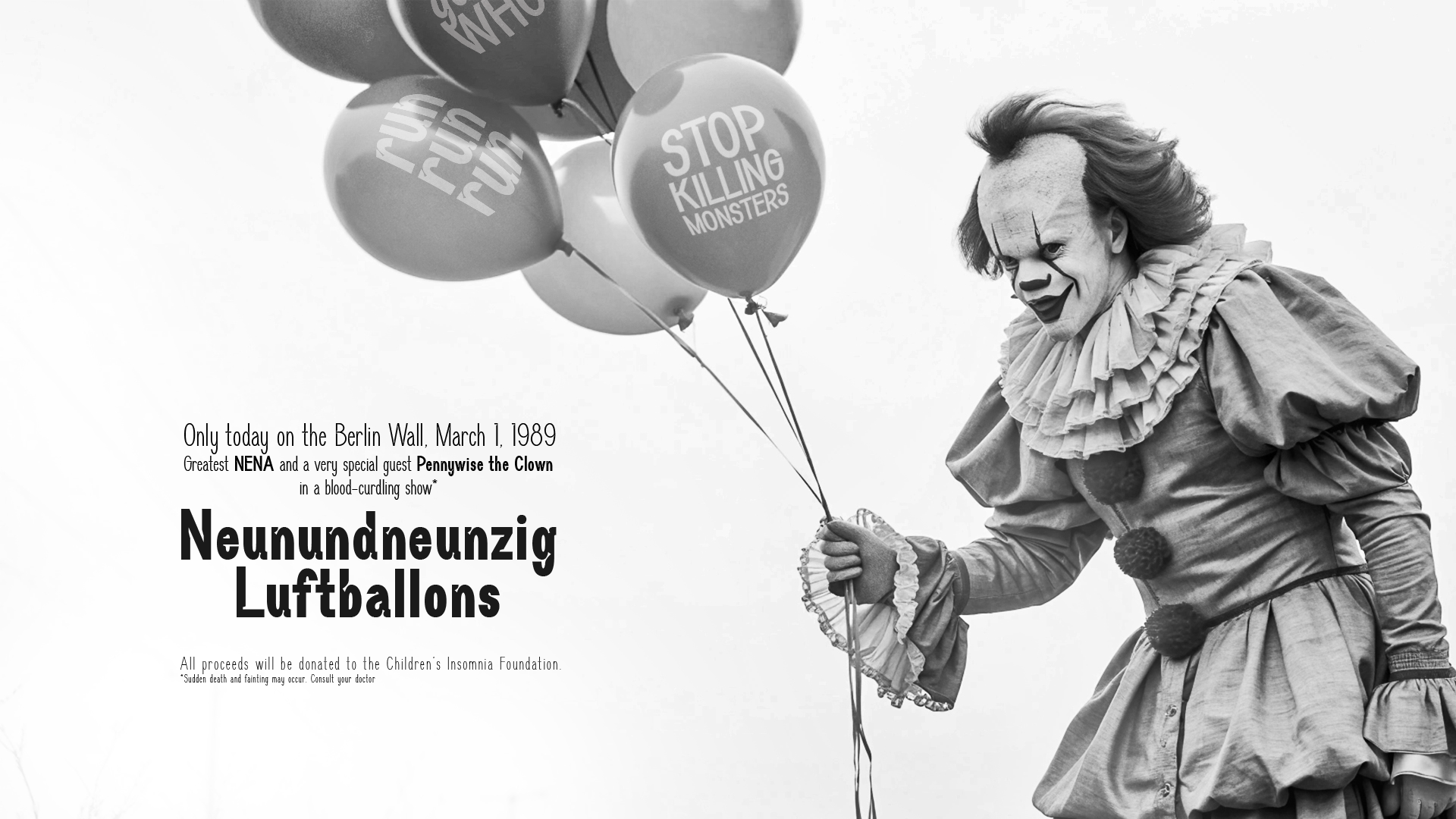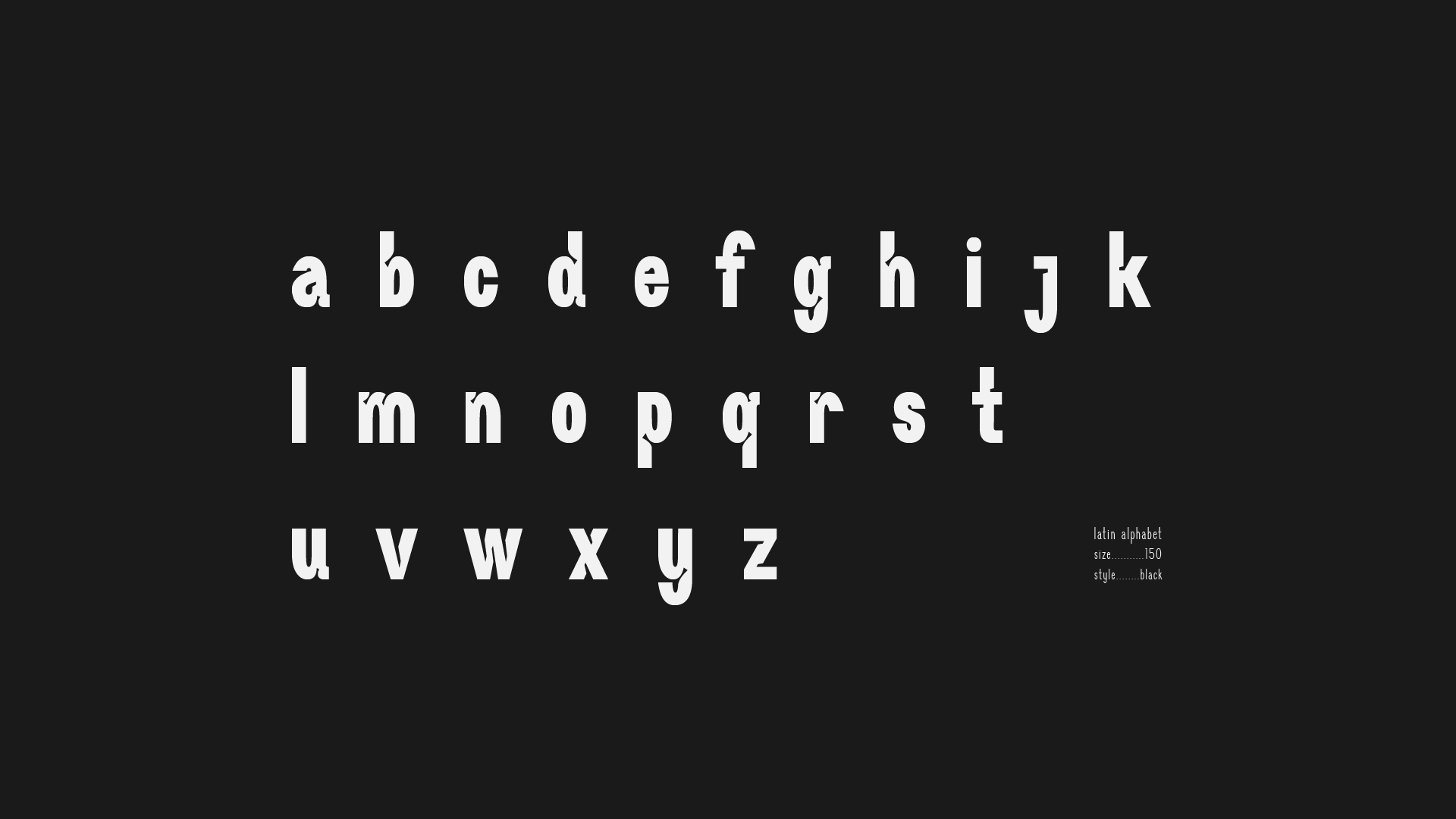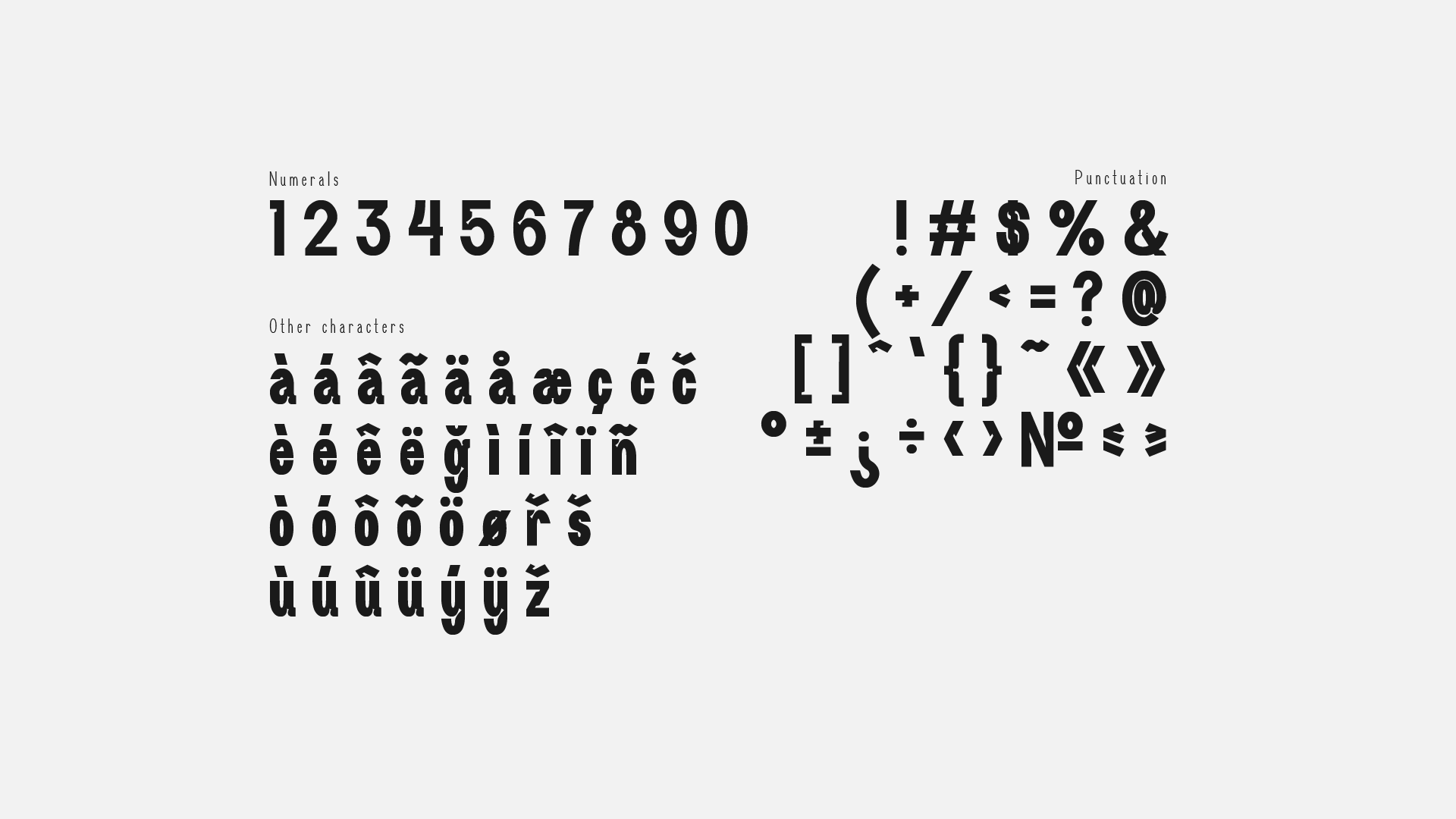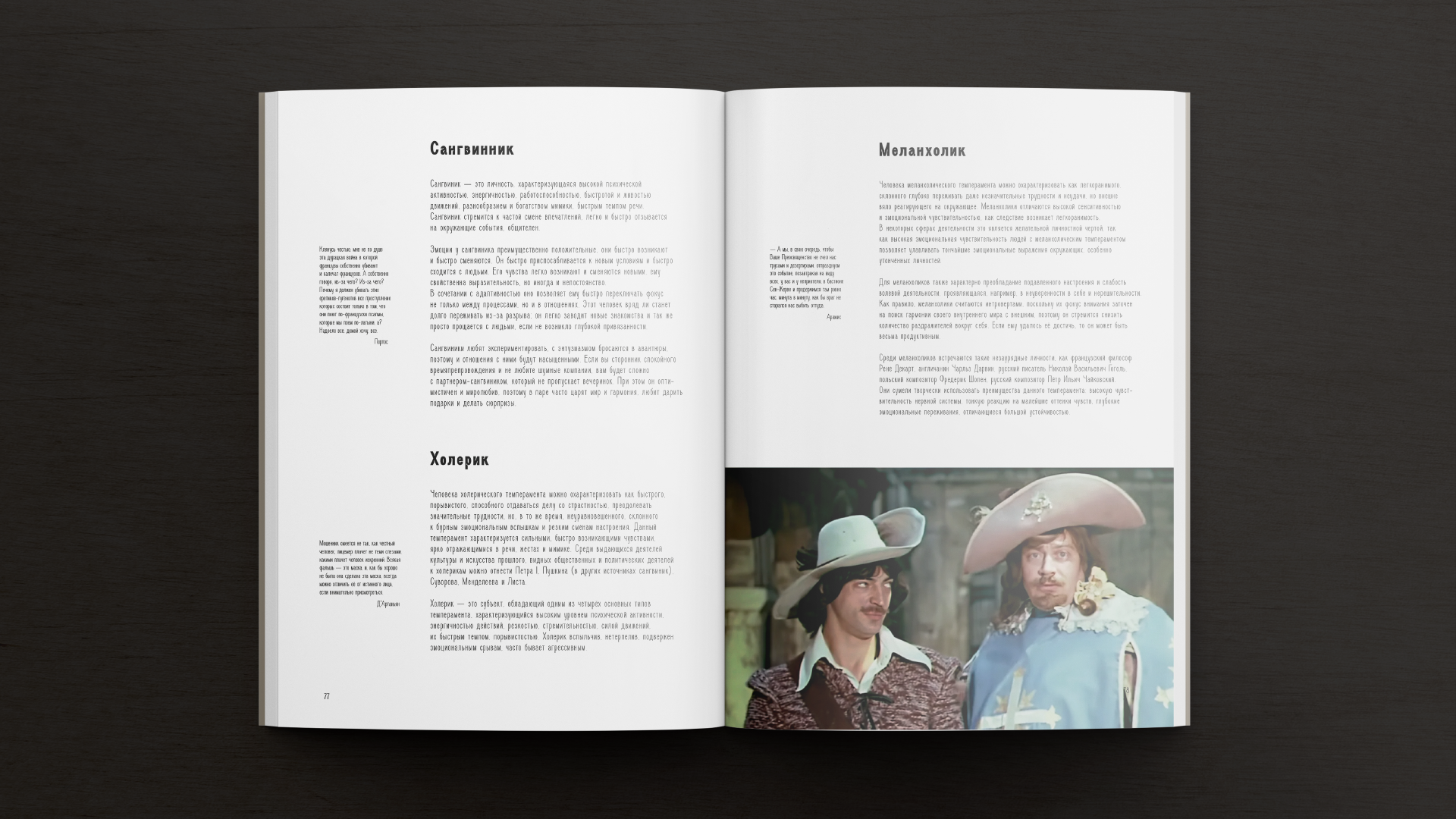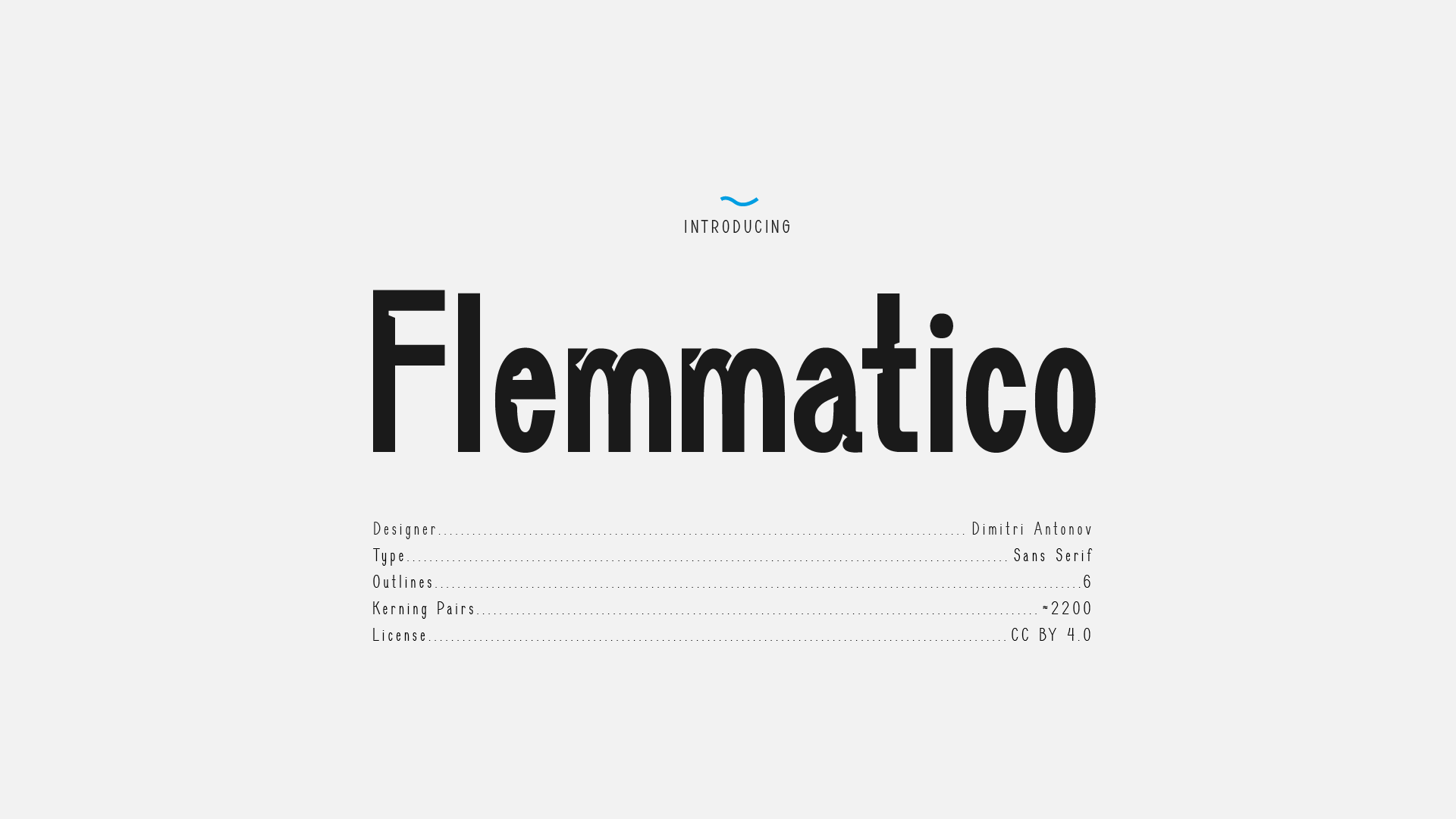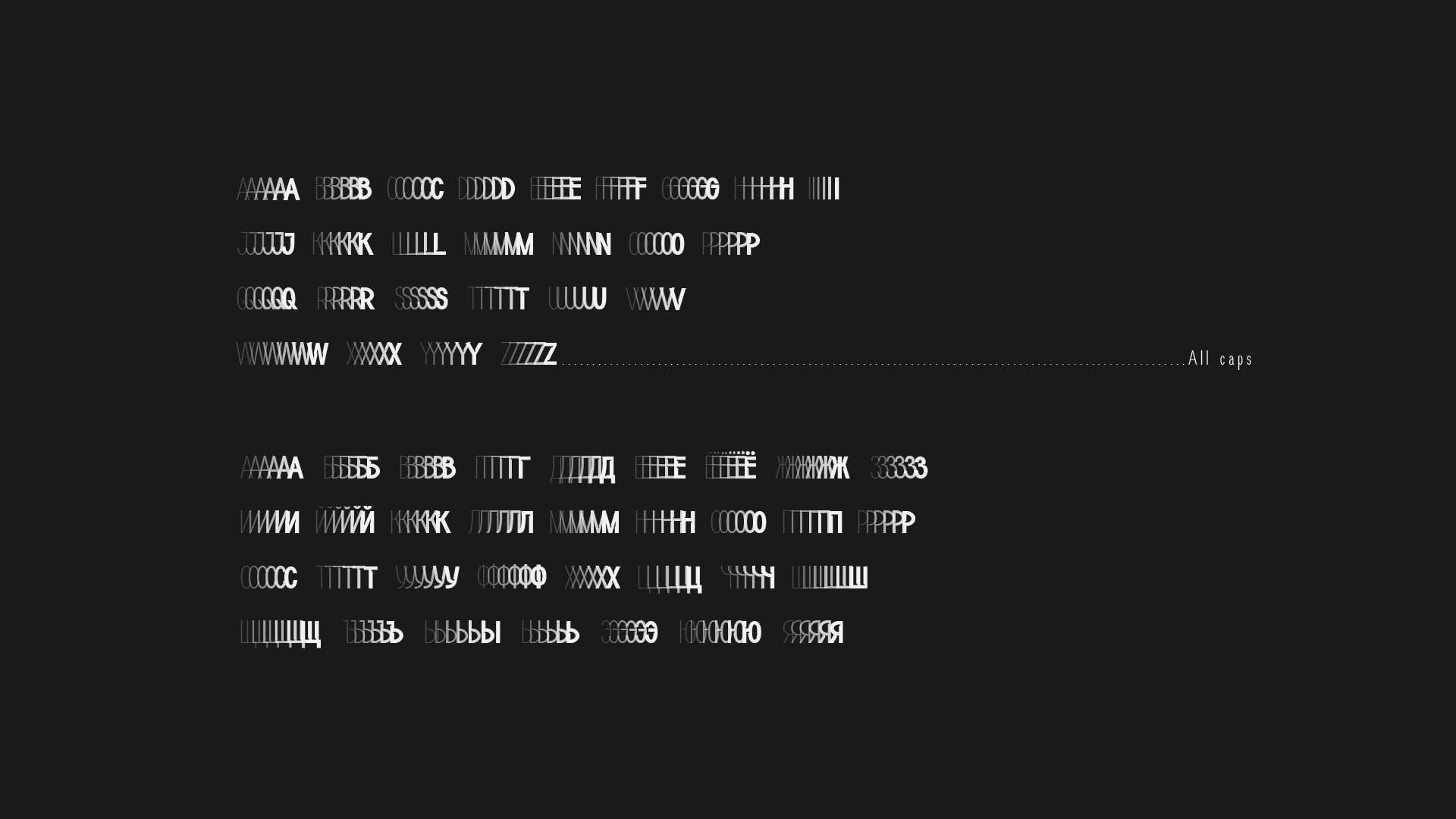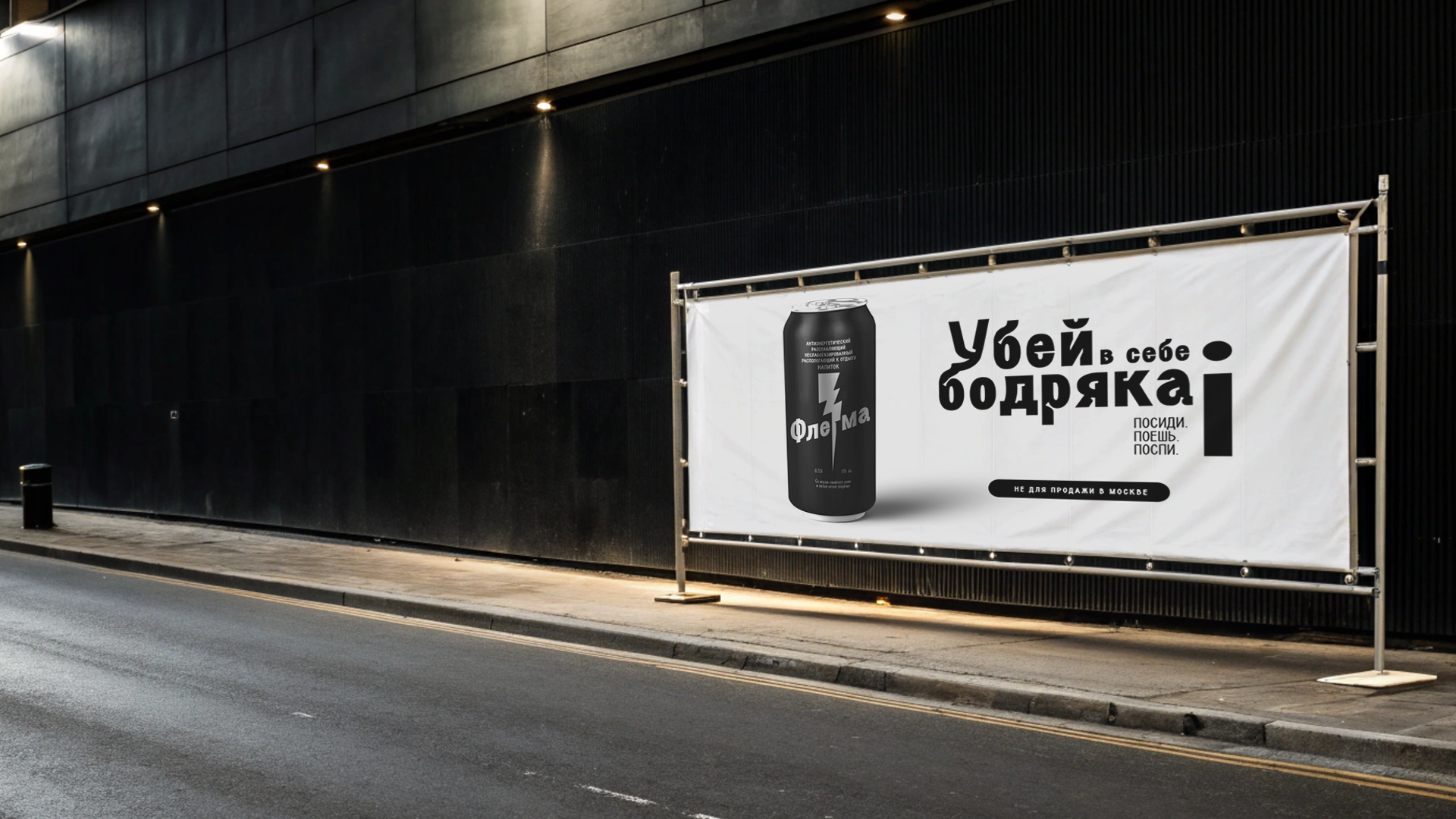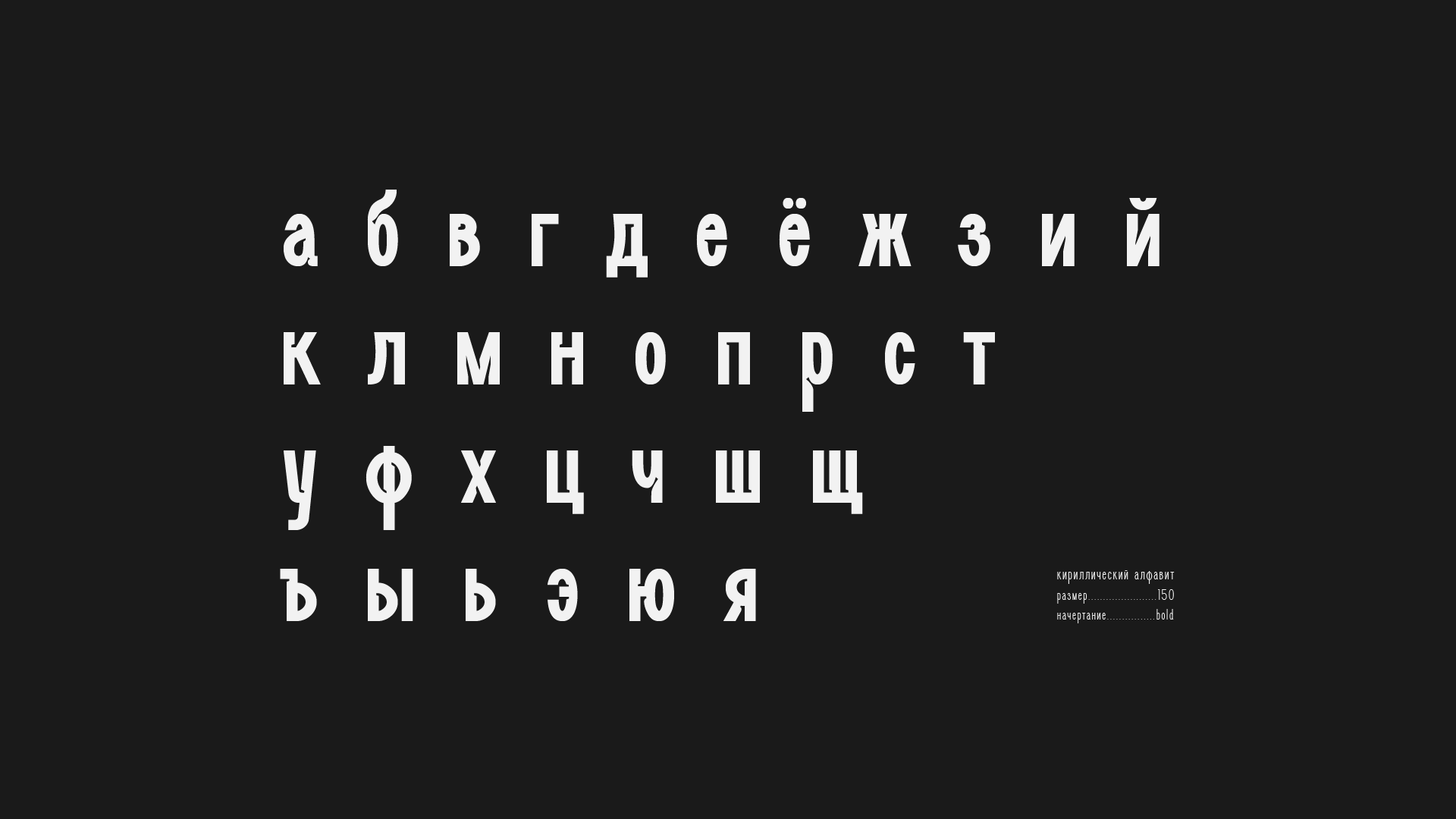
Тиражный шрифт
FLEMMATICO
Описание работы
Flemmatico - это спокойный антиурбанистический, органический гротеск, сочетающий в себе чистые формы и безупречную функциональность.
С его помощью можно спокойно создавать выразительные заголовки и комфортный для спокойного чтения текст.
В нём 260 спокойных символов, 6 относительно спокойных начертаний, спокойно работающих в 20 языках, а быть спокойным за свой внешний вид ему помогают более 2200 кернинговых пар.
Главное - сохранять спокойствие.